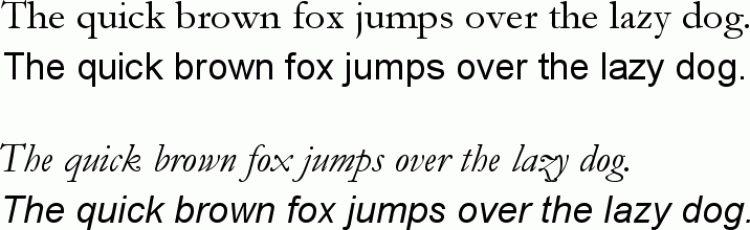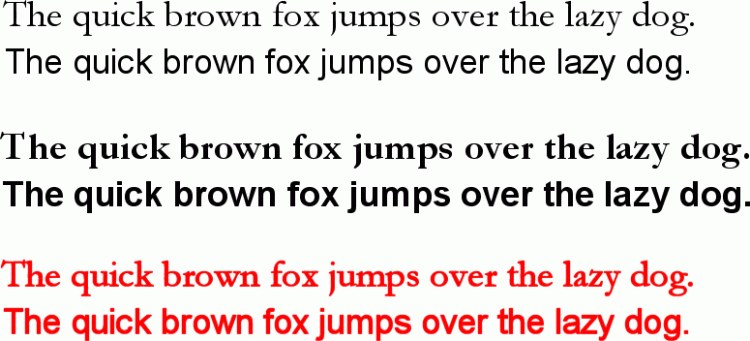
Die Varianten einer Schriftfamilie
Früher waren Schriftgestalter ausgebildete Künstler, oft von hoher Anerkennung. Heute glaubt das jeder Hobby-PC-Nutzer zu können und so sieht es dann oft auch aus. Ich will hier gar nicht dem Rückfall in vorindustrielle Zeiten mit der Zeichenfeder das Wort reden, aber schon die einfachsten Grundbegriffe werden oft durcheinandergebracht.
Beispielsweise stellen viele Programme für eine kursive Schrift einfach alle Zeichen schräg. Das ist falsch, denn die kursive Auszeichnung bildet einen eigenen Schriftschnitt innerhalb der jeweiligen Schriftfamilie. Am deutlichsten wird dies daran, dass einige Buchstaben sogar ganz anders konstruiert sind, wie das folgende Bild vor allem für die Antiqua-Schrift zeigt:
Schriftunterschiede für kursive Auszeichnung (von oben: Antiqua, Grotesk, Antiqua kursiv, Grotesk kursiv)
Auch die Unsitte, eine magere Schrift einfach mit einem dickeren Umriss in eine angeblich fette Schrift zu verwandeln, gehört zu der traurigen Realität.
Noch viel schlimmer war die bei Nadeldruckern übliche Technik, "fette" Schrift durch horizontal versetzten, wiederholten Ausdruck zu erzeugen. Die englische Bezeichnung Poor man's bold (des armen Mannes fette Schrift) gibt wieder, wie das wirkt.
Magere (oben), fette (Mitte) und fehlerhaft durch Umriss verdickte Schrift (unten, rot).
Wenn Sie im Windows-Fonts-Ordner nachsehen, werden Sie feststellen, dass zu einer guten Schrift tatsächlich mehrere Schrift-Dateien vorliegen, nämlich für magere, fette und kursive Auszeichnungen getrennt:
Der Einsatz von Schriften im Alltag
Wenn Sie nicht gerade ein Logo entwerfen (siehe "Logo gestalten - Wie Sie schnell und einfach Ihr eigenes Logo entwickeln"), geht es meistens um Massentexte und deren Überschriften, beispielsweise für Flyer. Die goldene Regel dabei heißt: Wenige Schriften, aber mit deutlichen Unterschieden! Typischerweise kommen Sie dabei mit zwei Schriften aus, etwa einer fetten Grotesk für die Überschriften und einer mageren Antiqua für den Lauftext.
Obwohl es durchaus üblich ist, eine Grotesk und eine Antiqua gleichzeitig einzusetzen, können Sie natürlich auch überall die gleiche Schriftart nutzen. Dann sollten die Überschriften aber nicht nur merklich größer, sondern auch fett sein, damit ein ausreichender Unterschied zu erkennen ist.
Schrift für Code
Nur ausnahmsweise kommt eine dritte Schrift in Frage, etwa um Code zu kennzeichnen. Da Programmcode nicht nur nach ästhetischen Gesichtspunkten beurteilt wird, sondern oft bestimmte Einrückregeln hat, wird hier eine nicht-proportionale Schriftart bevorzugt. Eine solche ("äquidistant" genannte) Schrift ist beispielsweise die Courier New Roman.
Daher finden Sie oft Schriften, die ganz knapp neben dem Original liegen. Oftmals sind die Unterschiede mehr juristischer als optischer Natur, wie das folgende Beispiel zeigt:
Helvetica Roman
Swiss721 (die Rundungen sind breiter)
Da der Name ebenfalls geschützt ist, heißen die Schriften dann nicht Helvetica, sondern Swiss oder Times New Roman anstatt einfach nur Times.
Times
Times New Roman (die Abstände sind größer)
Schriften installieren
Wenn Sie eine neue Schrift installieren wollen, ist es inzwischen erfreulich einfach. Sie erhalten beim Download eine TTF-Datei und schieben diese mit gedrückter Maus in das Verzeichnis C:\Windows\Fonts\ (oder den entsprechenden Pfad, wenn Windows bei Ihnen anders installiert ist). Dann erscheint kurz der Dialog wie im folgenden Bild und das war's schon.